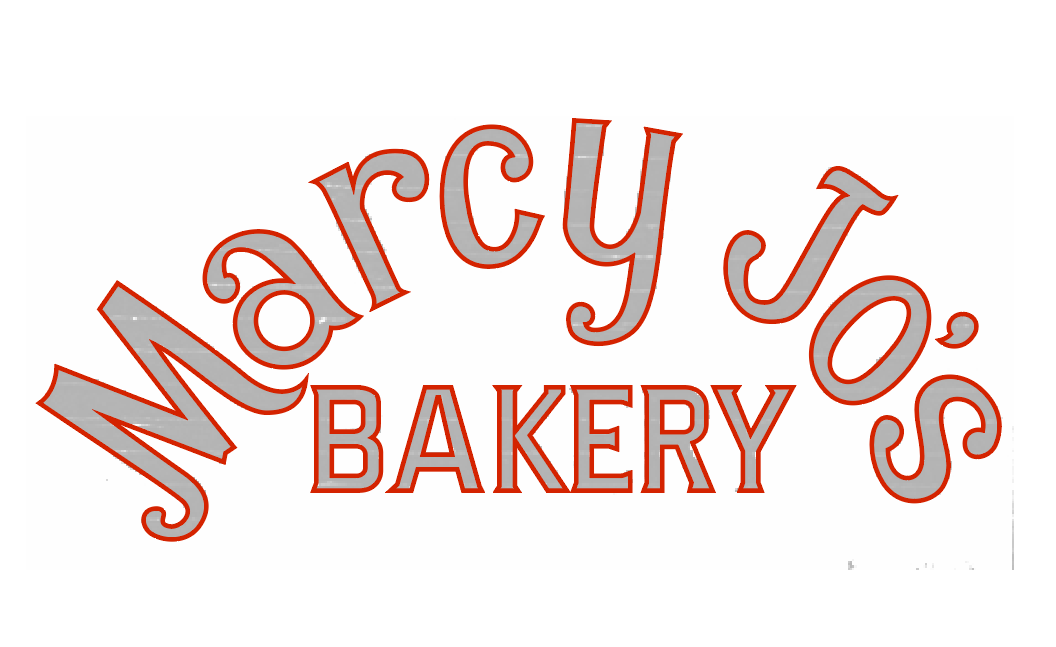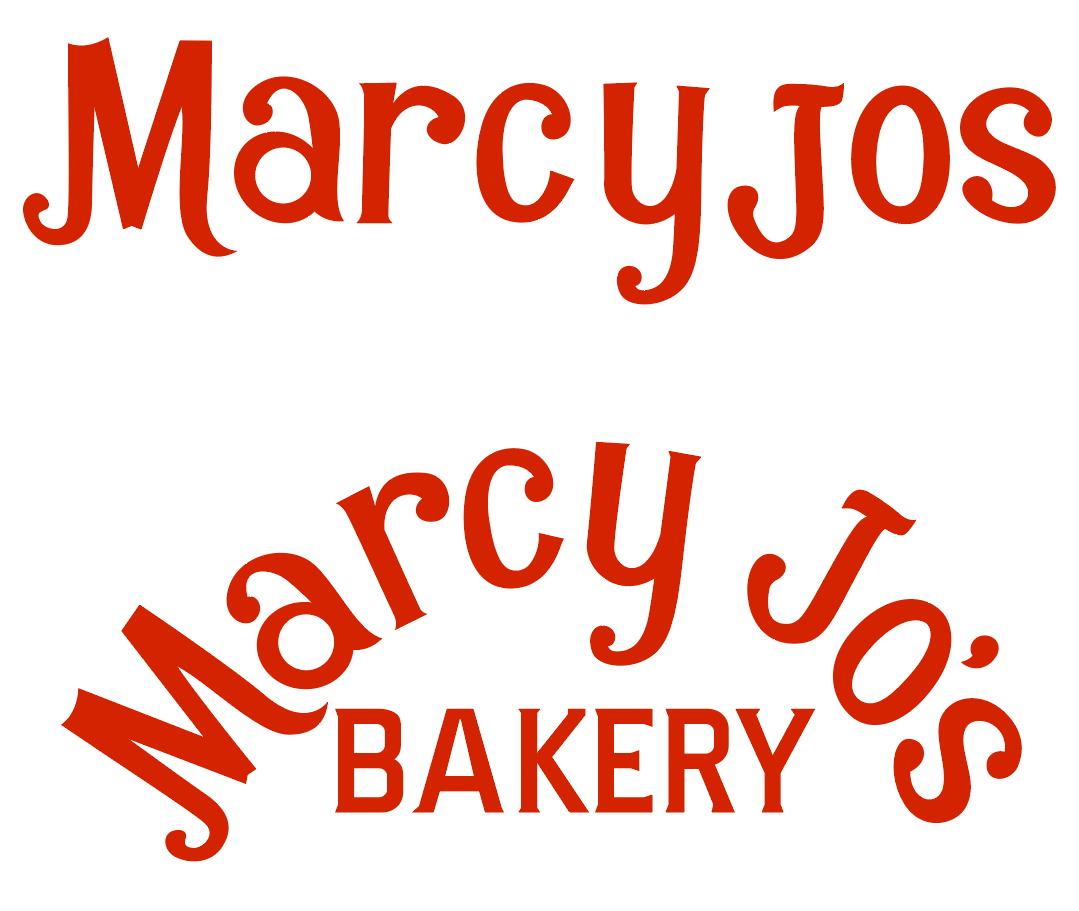
මේ font එක මොකද්ද කුකුලෝ?
Marcy Jo's එක
Did it anyways for fun, use this to find a similar font machan
What the font is a website i used back then. this is a hand drawn one.